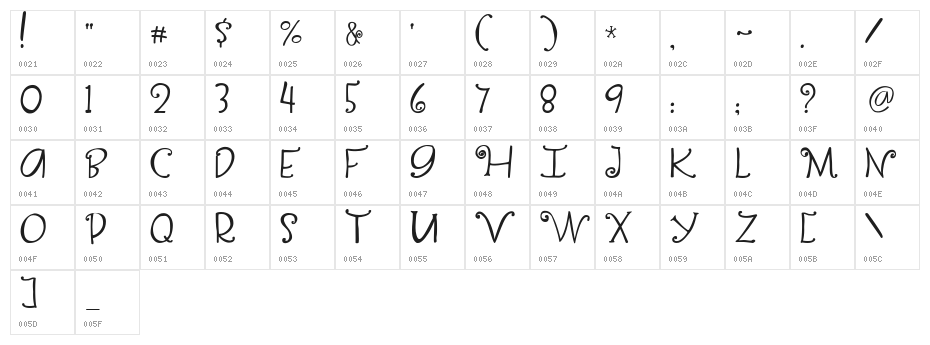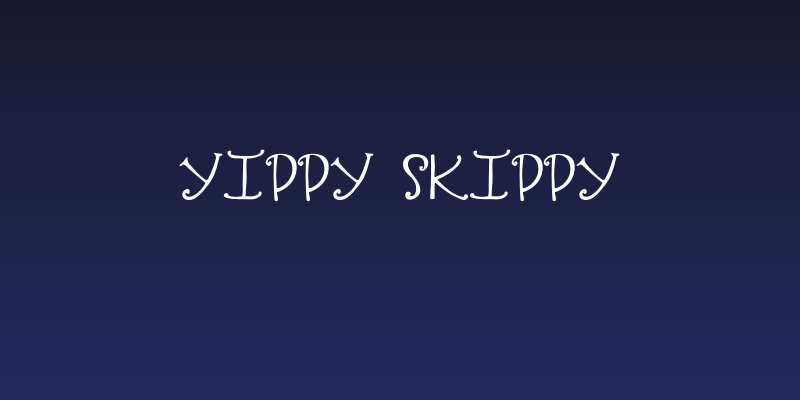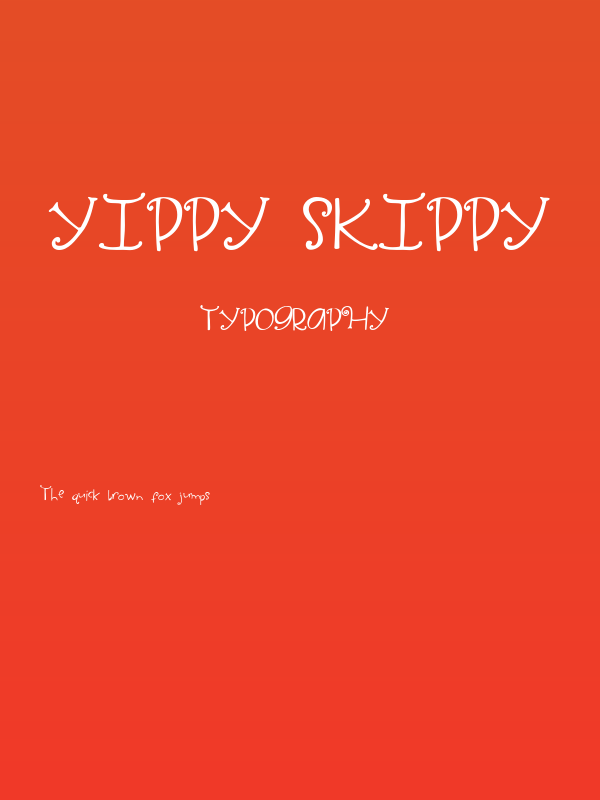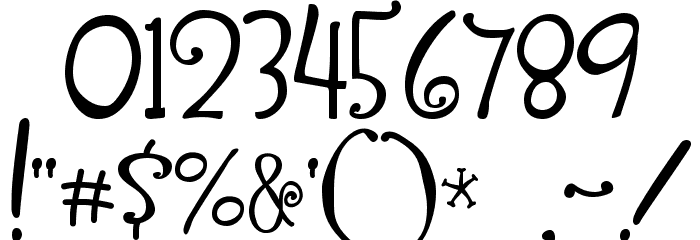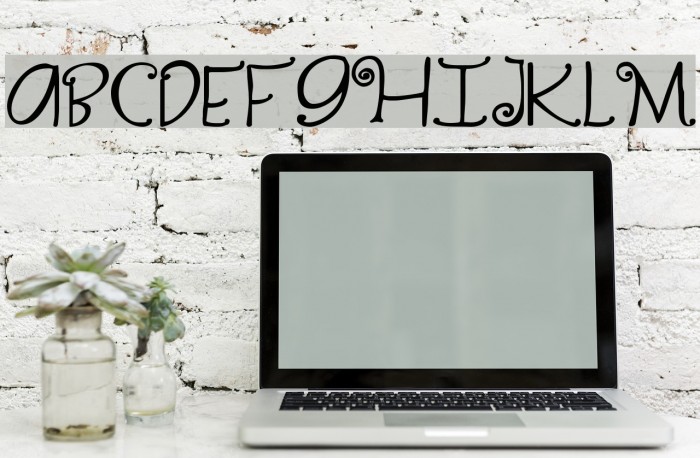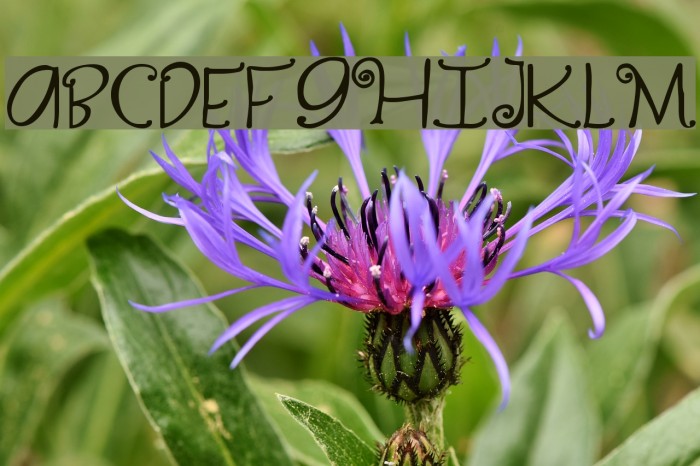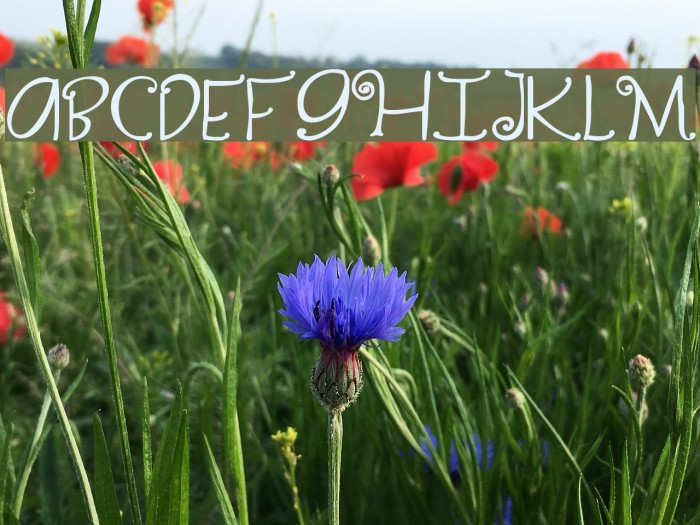
Yippy Skippy Font
| Gesamtstil | Whimsical, Playful |
| Anwendungsfall | Headlines, Logos, Creative projects |
| Vorgeschlagene Projekte | Ideal for children's books, playful branding, greeting cards, and creative invitations. |